Bệnh nhân bước vào phòng khám và ánh mắt họ thường dừng lại vài giây trên vùng ngực áo bác sĩ. Nếu dòng chữ thêu chức danh bị nhòe hoặc font chữ thiếu sự chỉn chu, niềm tin vào năng lực chuyên môn của người đối diện sẽ giảm đi đáng kể. Đây không chỉ là vấn đề thẩm mỹ. Font chữ thêu trên blouse chính là tín hiệu tin cậy đầu tiên mà bệnh nhân nhận được khi tiếp cận bác sĩ, đặc biệt với các chức danh cao cấp như PGS.TS hay BS.CKII. Sự sắc nét của đường chỉ và cấu trúc ký tự phản ánh trực tiếp mức độ chuyên nghiệp của cơ sở y tế. Một vết thêu kém chất lượng có thể làm mờ đi mọi nỗ lực xây dựng hình ảnh chuyên môn của đội ngũ.
Tại sao blouse là ‘phép thử’ cho font chữ thêu chức danh?
Áo blouse trắng không chỉ là trang phục, mà là tuyên ngôn về vị thế chuyên môn. Trong khi bộ scrubs tối ưu cho sự linh hoạt khi di chuyển và thực hiện thủ thuật, blouse cổ bẻ hay cổ đứng dành cho bác sĩ tư vấn và trưởng khoa lại đòi hỏi sự trang trọng, chỉn chu tuyệt đối.
Bệnh nhân thường đánh giá uy tín của bác sĩ qua những chi tiết nhỏ nhất trên trang phục. Một dòng thêu chức danh bị nhòe hay font chữ thiếu sắc sảo sẽ ngay lập tức khiến họ hoài nghi về sự chuyên nghiệp của cơ sở. Đó là lý do tại sao việc chọn mẫu thêu tên lại quan trọng không kém gì quy trình y khoa.
Nhiều đơn vị y tế vẫn mắc phải sai lầm phổ biến là áp dụng một bộ nhận diện thêu chung chung cho toàn bộ nhân viên. Cách làm này vô tình xóa nhòa ranh giới cần thiết giữa các cấp bậc, làm giảm đi sự khác biệt vốn có của các chức danh cao. Sự đồng nhất cần được thể hiện ở thương hiệu, nhưng sự phân cấp phải được thể hiện rõ qua font chữ thêu và cách bố trí thông tin trên áo.
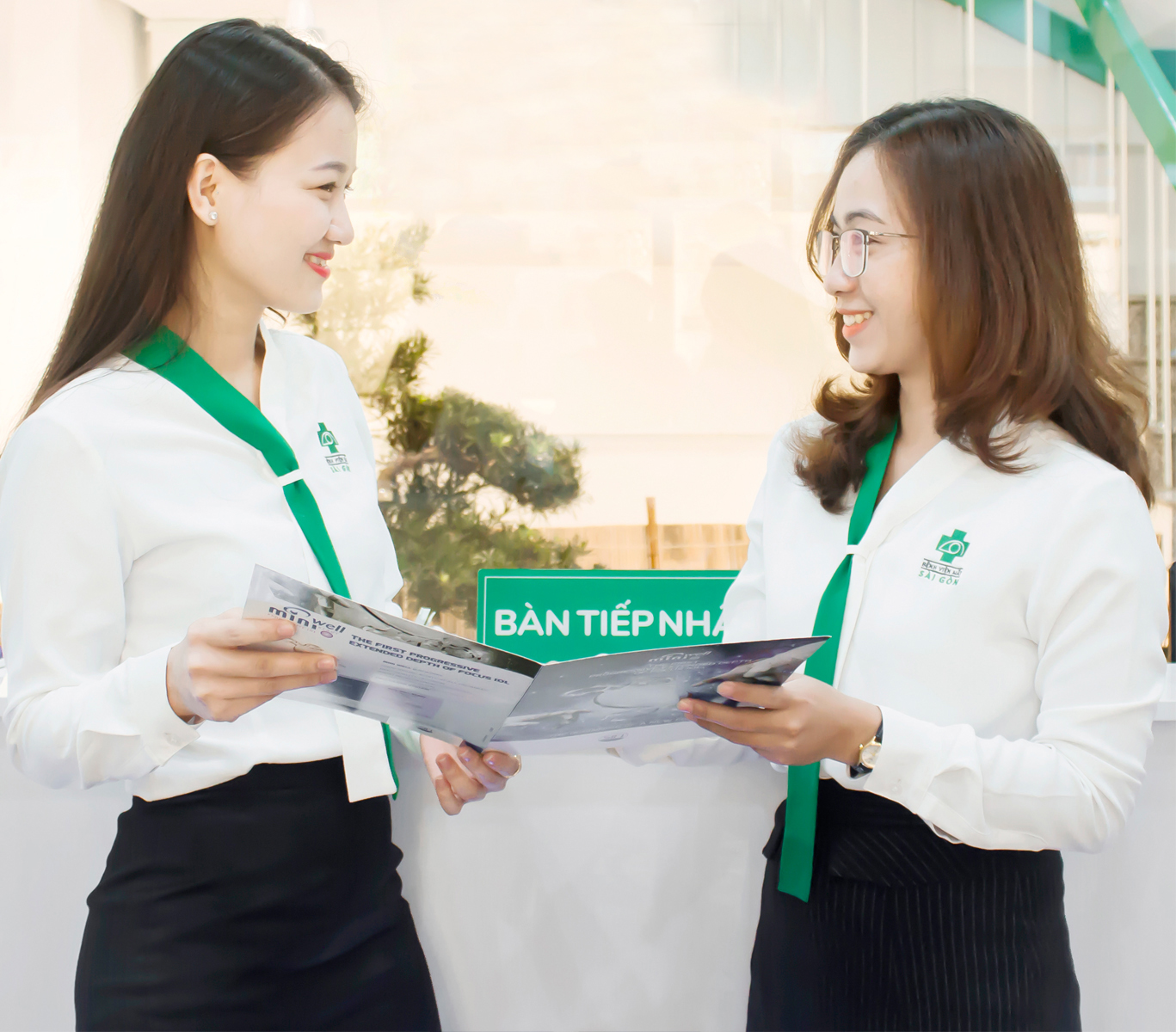
Khi chúng ta quan sát một bộ đồng phục, độ sắc nét của đường kim mũi chỉ phản ánh trực tiếp văn hóa quản lý của bệnh viện. Một vết thêu chính xác không chỉ làm đẹp mà còn là lời cam kết vô hình về sự an toàn. Do đó, việc đầu tư vào chất lượng thêu là một phần không thể thiếu trong trải nghiệm khách hàng, giúp tăng cường uy tín và tạo ấn tượng tích cực ngay từ lần đầu tiên.
Serif hay Sans-serif: Font chữ thêu phù hợp với vị thế chuyên môn
Việc lựa chọn font chữ thêu cho blouse không đơn thuần là vấn đề thẩm mỹ, mà là cách định vị vai trò của người mặc trong mắt bệnh nhân. Nhóm font Serif (có chân chữ) mang lại cảm giác trang trọng, học thuật và ổn định, rất phù hợp với các chức danh cao cấp như PGS.TS hay Trưởng khoa. Ngược lại, nhóm font Sans-serif (không chân) truyền tải sự hiện đại, nhẹ nhàng và dễ tiếp cận, hợp hơn với điều dưỡng, y tá hoặc sinh viên thực tập.
Sự khác biệt này thể hiện rõ qua hình dáng từng nét chữ: chân chữ giúp dòng chữ đứng vững và có trọng lượng thị giác, trong khi sự trơn tru của Sans-serif tạo cảm giác nhanh gọn, thân thiện. Khi áp dụng cho thêu chức danh y, điều này giúp tránh việc dòng chữ “trội” hay “lọt thỏm” so với vai trò thực tế.
Độ nét cao là yêu cầu kỹ thuật bắt buộc. Khi thêu vi tính, các đường nét mỏng hoặc quá phức tạp có nguy cơ dính vào nhau, làm chữ bị nhòe ở kích thước nhỏ. Một mẫu thêu tên tốt phải giữ được tính sắc nét ngay cả khi chỉ chạy trên nền vải cotton hay kate.
Cần tránh xa các font quá trang trí hoặc thân chỉ quá mảnh. Những thiết kế này thường khó đọc trên nền vải blouse, đồng thời tạo cảm giác thiếu chuyên nghiệp, làm giảm độ tin cậy mà cơ sở y tế muốn truyền tải.
Kỹ thuật thêu: Bí quyết để chữ thêu blouse trông ‘đắt’ và bền bỉ
Độ sắc nét của chữ thêu không chỉ phụ thuộc vào font chữ, mà còn quyết định bởi mật độ mũi kim và chất lượng chỉ. Với môi trường y tế, nơi trang phục thường xuyên tiếp xúc với hóa chất khử trùng, kỹ thuật thêu vi tính là lựa chọn tối ưu. So với thêu tay hoặc in dán, công nghệ này đảm bảo độ nổi của các nét chữ và khả năng giữ form vải nguyên vẹn sau hàng chục lần giặt công nghiệp.
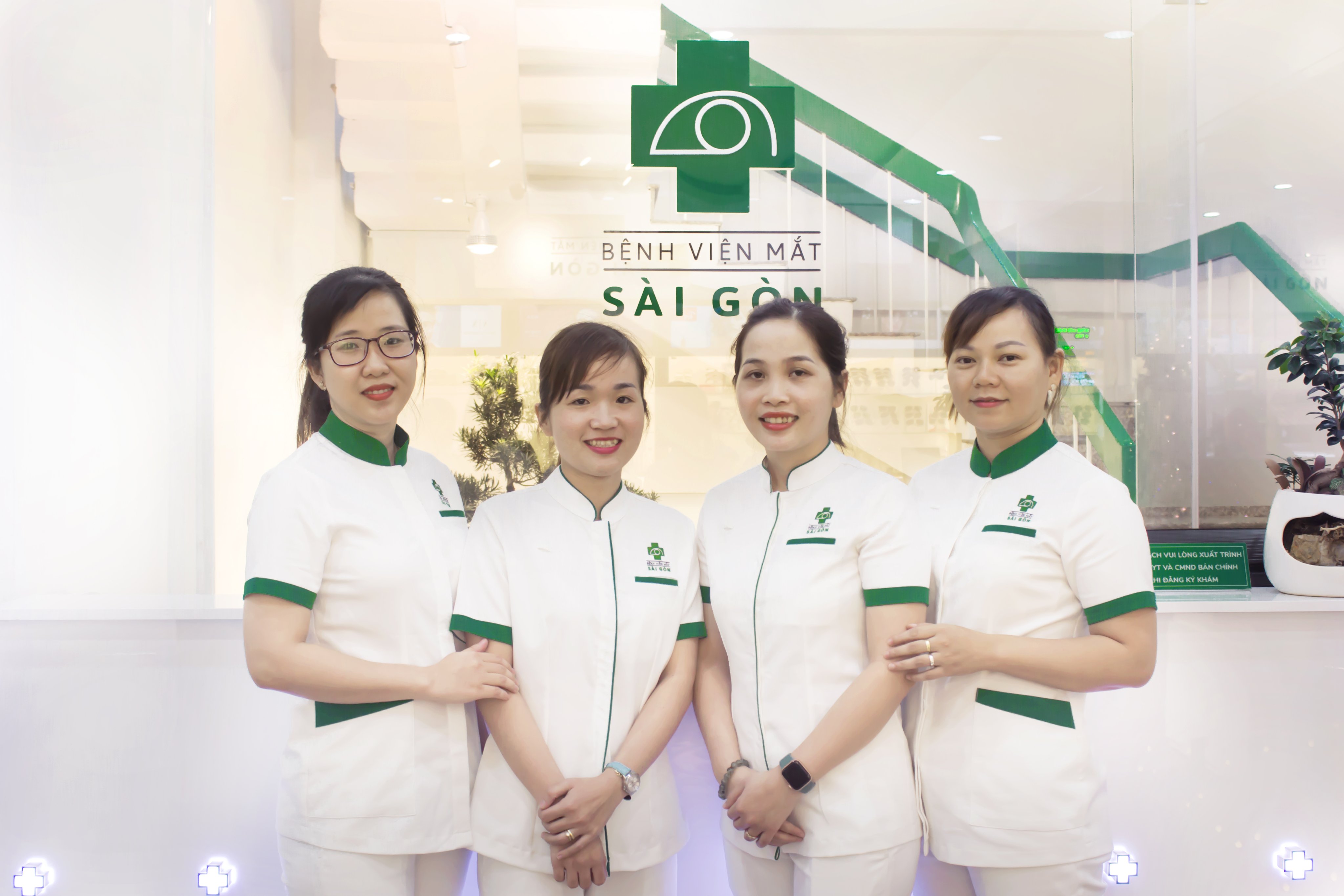
Tuy nhiên, một lỗi kỹ thuật phổ biến khiến mẫu thêu tên trên blouse mất đi sự trang trọng là mật độ chỉ không đồng đều. Khi mật độ chỉ quá dày, bề mặt thêu sẽ trở nên cứng, gây cảm giác cộm và khó chịu cho người mặc trong suốt ca trực. Ngược lại, nếu chỉ quá mỏng, các chi tiết nhỏ của font chữ sẽ bị mờ đi chỉ sau vài lần giặt khử trùng, làm giảm tính chuyên nghiệp của bộ đồng phục.
Chiều cao chữ là yếu tố then chốt để đảm bảo tính thẩm mỹ và khả năng đọc. Với thêu chức danh y và tên bác sĩ, mức tiêu chuẩn thường rơi vào khoảng 8–10mm. Kích thước này đủ để người đối diện nhận diện rõ ràng từ khoảng cách 1 mét, nhưng không quá lớn để phá vỡ sự cân đối của vùng ngực áo. Một mẫu thêu tên đạt chuẩn cần có sự hài hòa giữa độ dày của nét chỉ và khoảng cách giữa các ký tự, giúp thông tin hiển thị mạch lạc trên nền vải trắng hay màu pastel.
Đồng nhất nhận diện: Khi thêu tên và logo cùng một giọng điệu
Sự liền mạch trong hình ảnh không đến từ việc thêm chi tiết, mà từ việc giữ đúng “giọng điệu” thương hiệu. Nếu logo bệnh viện được thiết kế theo phong cách serif với các nét chân vững chãi, thì dòng thêu tên blouse ghi chức danh bác sĩ bên cạnh cũng nên cùng hệ font. Sự đồng bộ này giúp bệnh nhân nhận diện thương hiệu tức thì, biến chiếc blouse thành một phần của bộ nhận diện tổng thể thay vì chỉ là đồng phục cá nhân.
Một dòng thêu chức danh chính xác và chỉn chu không chỉ là chi tiết thẩm mỹ trên blouse, mà là lời cam kết im lặng về sự an toàn và chuyên nghiệp dành cho bệnh nhân. Khi mỗi đường kim mũi chỉ thể hiện sự tôn trọng đối với vị thế của người mặc, niềm tin của người đối diện cũng được nâng lên một bậc. Nếu phòng khám của bạn đang tìm kiếm giải pháp đồng phục y tế đảm bảo kỹ thuật thêu nghiêm ngặt và tính thẩm mỹ, việc tham khảo tư vấn từ các đơn vị chuyên sâu như Đồng phục Hoa Tay có thể giúp bạn đưa ra lựa chọn phù hợp nhất cho đội ngũ y bác sĩ.